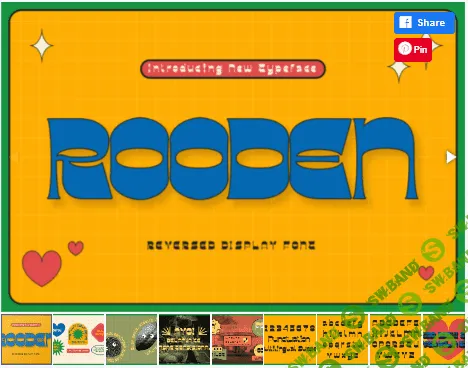
Название: Rooden Font (2022)
[creativefabrica] Rooden Font (2022)
Rooden — это перевернутый дисплейный шрифт, идеально подходящий как для печати, так и для цифровых нужд. Это сделает ваши творения более привлекательными, веселыми и красивыми!